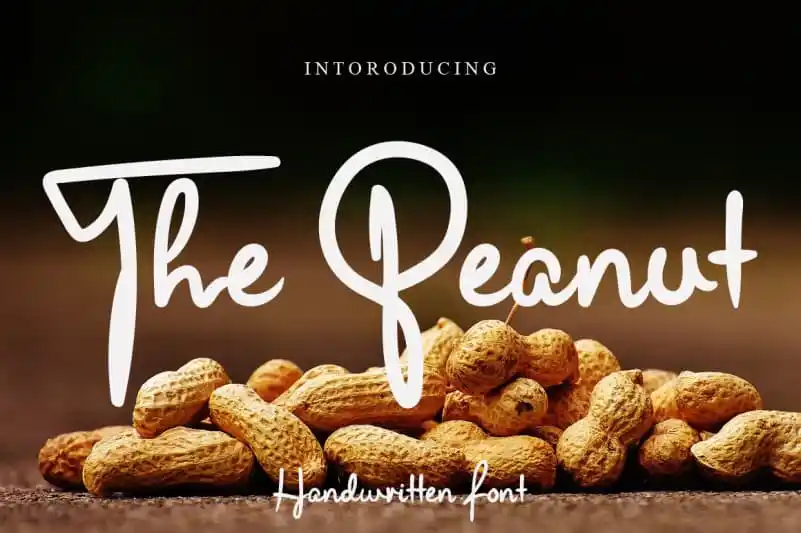
The Peanut Script Font – Download Grátis
A The Peanut Script Font é uma elegante e fresca tipografia escrita à mão desenhada com traços suaves do pincel. Seu estilo natural e único a tornam ideal para um amplo leque de designs, desde logotipos até materiais de marketing e design gráfico em geral. Essa fonte é perfeita para quem procura algo leve que seja capaz de dar um toque sofisticado a qualquer projeto, enquanto mantém uma atmosfera descontraída e criativa. Experimente essa bela fonte e explore suas infinitas variações – tenha sempre muito prazer com ela.